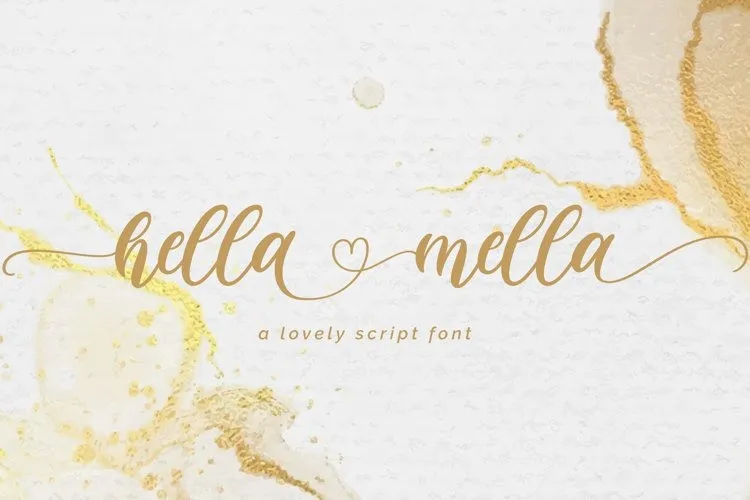
Hella Mella Font – Fonte Grátis
Hella Mella Font
Esta é uma fonte script relaxada e flutuante criada pelo designer FallenGraphic Std. Ideal para designers que valorizam flexibilidade e originalidade na produção de projetos, essa fonte se sobressai ao oferecer versatilidade para diversos tipos de design. Seus traços fluidos são perfeitos para criar convites de casamento memoráveis, arte elegante em cartões de visita, postagens chamativas nas redes sociais e até mesmo cartazes criativos para seus clientes. A fonte transmite uma sensação genuína do texto à mão, tornando-a a escolha ideal para quem busca um toque autêntico e único para seu próximo projeto visual. Seja você um profissional da área ou simplesmente alguém que adora criar designs únicos em casa, essa fonte é certamente o item que está buscando para dar vida à sua próxima ideia criativa. Não hesite em experimentar a Hella Mella Font em seus projetos e descubra por si mesmo como ela pode transformá-los no próximo grande hit!